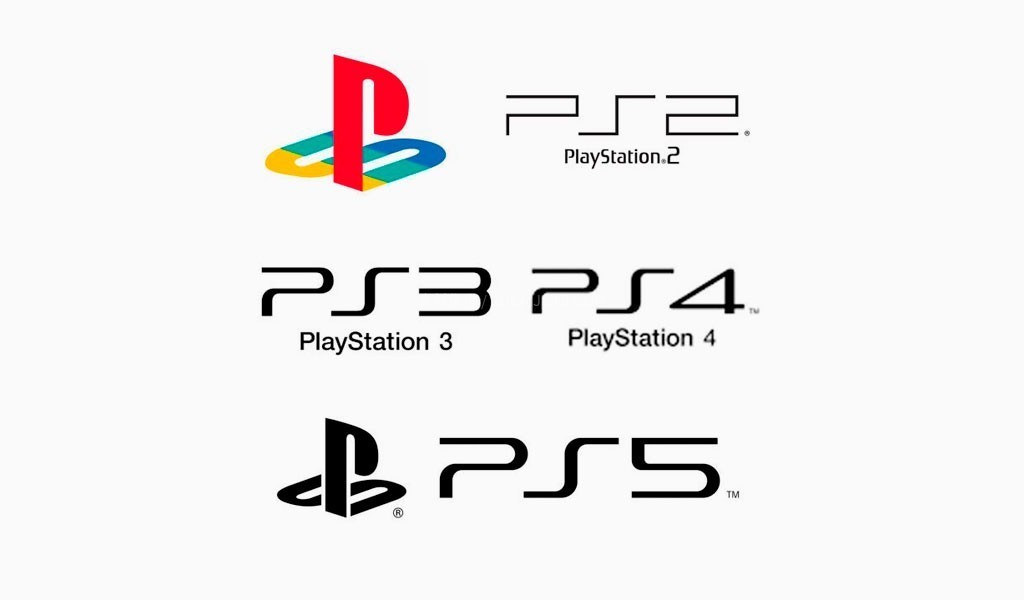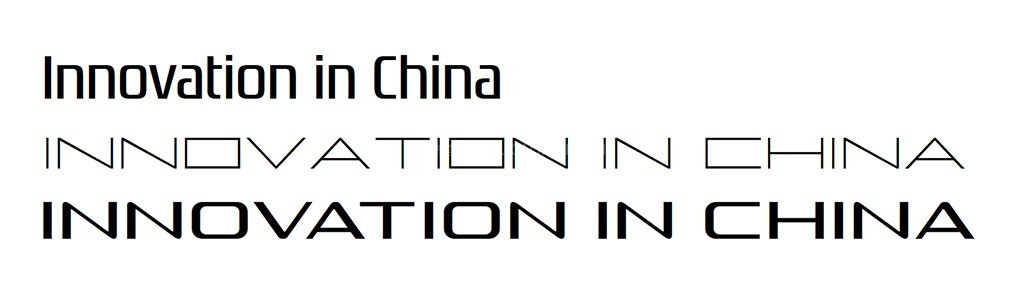
PlayStation索尼游戏LOGO标志字体复刻版
PlayStation 经典游戏 LOGO 标志字体合集,3款复刻了经典 PS 游戏机 LOGO 的极简与科幻线条,极具标志性的字母结构,直接把科技感拉满!不管是做游戏海报、电竞战队视觉,还是潮流外设的包装设计,用它排版简直绝绝子,一秒带你穿越回热血的主机游戏时代!